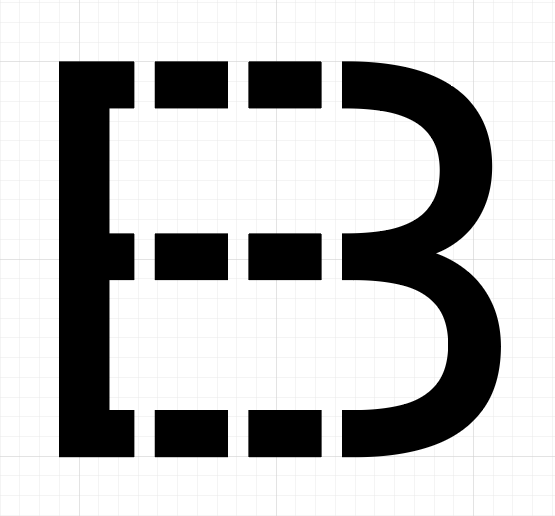
Modulare Schrift gesucht (weiter Schriftschnitt)
kennt ihr eine Schriftart, die so was drauf hat?
Man hat ein Anfangsteil und ein Endteil und in der Mitte kann man unendlich viele horizontale Striche dazu packen?
In die Horizontale könnte das ja auch funktionieren.